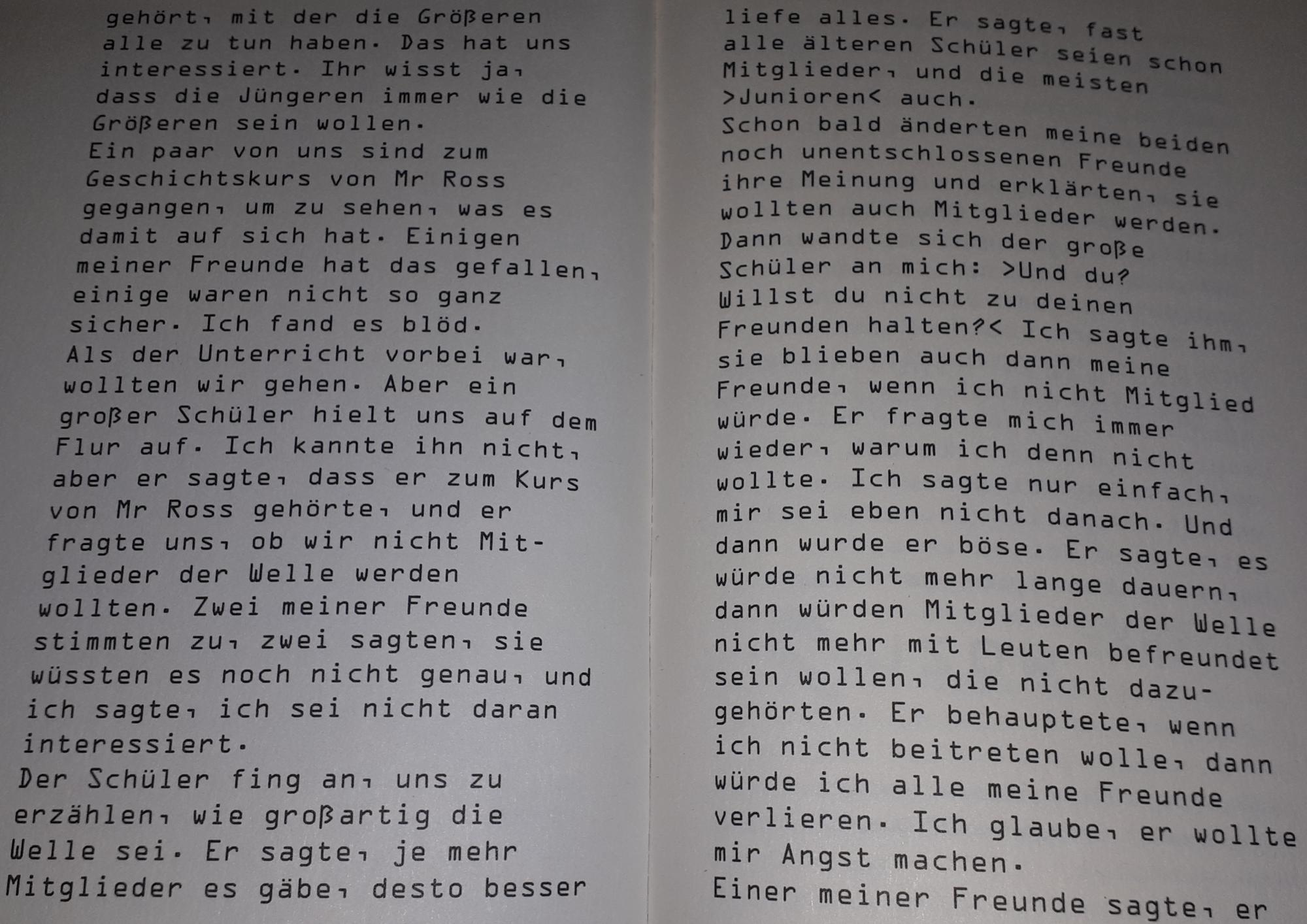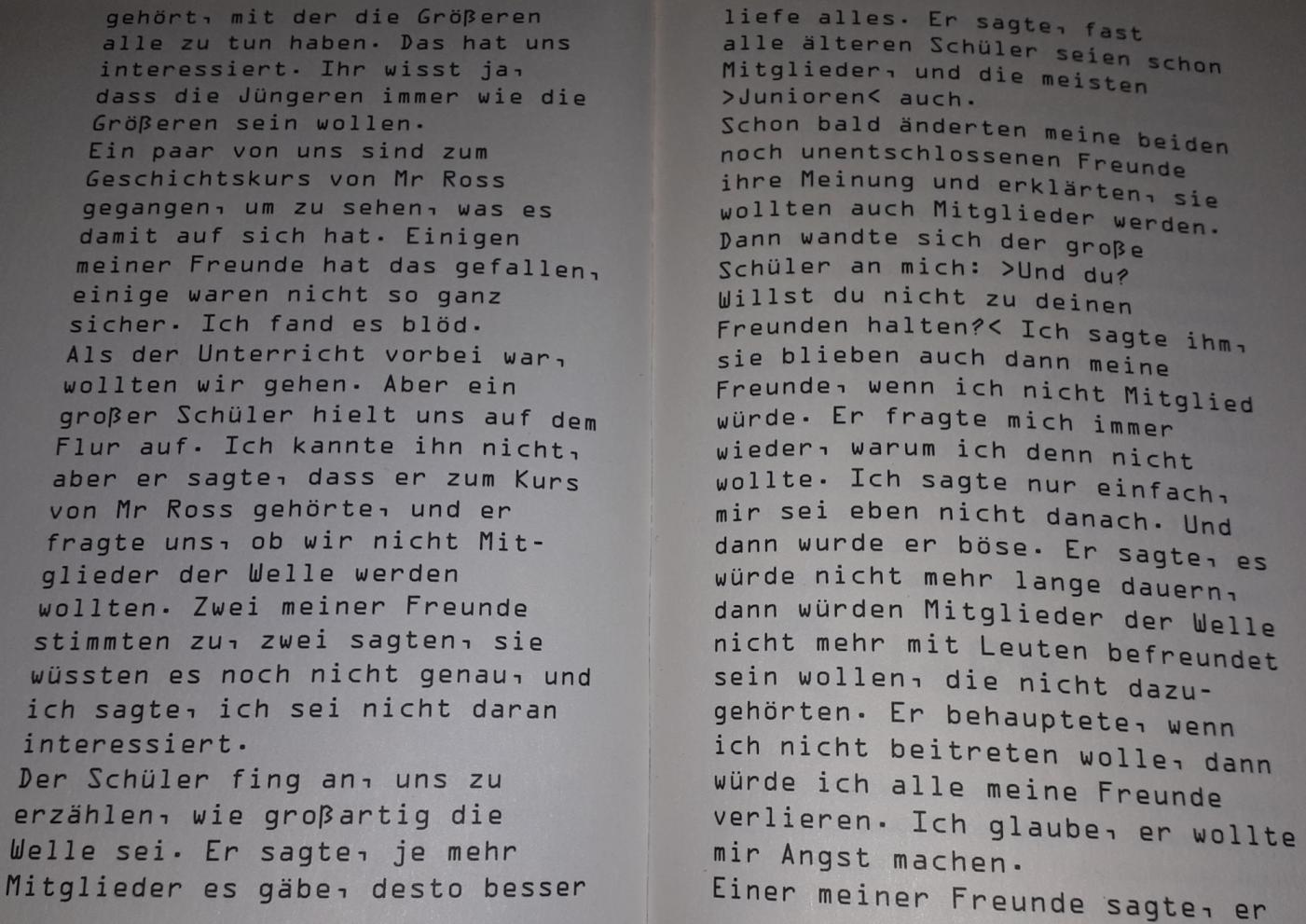
Wie heiß die Schriftart die im Buch "Die Welle" von Seite 108 - 109?
Ist das ß im gezeigten Beispiel nicht eh aus einer anderen Schriftart? Es steht ja viel zu weit links im Wort.
War im originalen Design überhaupt ein ß enthalten?
Jene Formen hab ich auf die Schnelle gefunden:
(obere drei: Linotype, untere: Adobe Fonts)